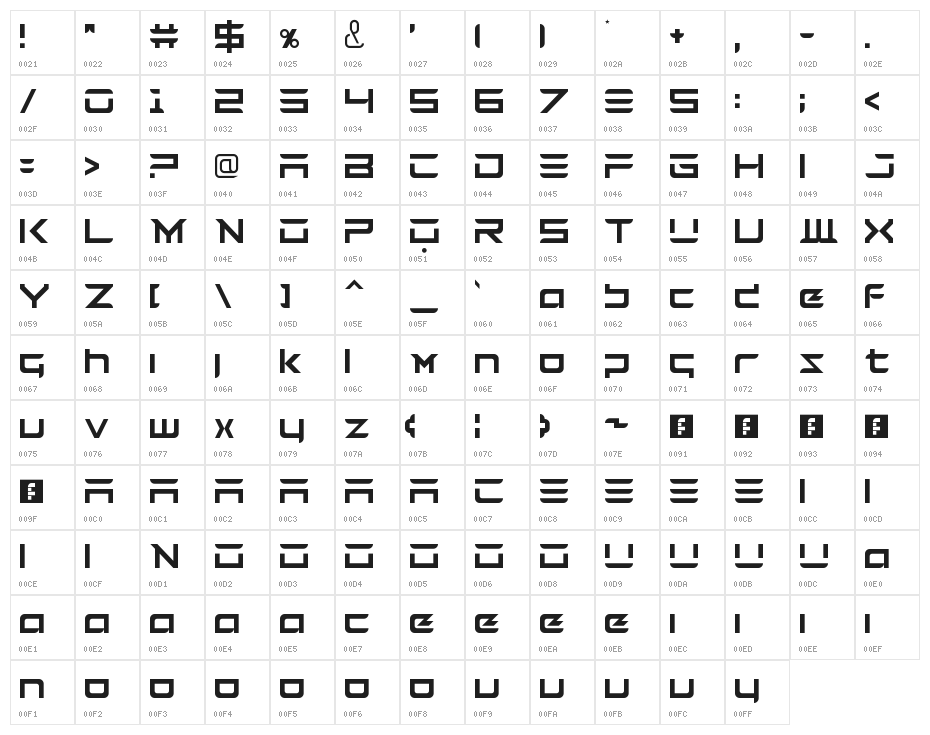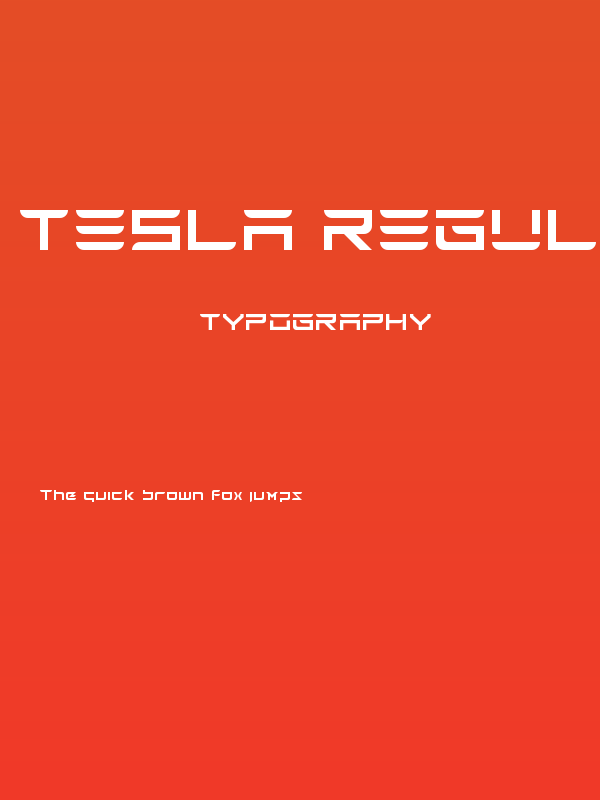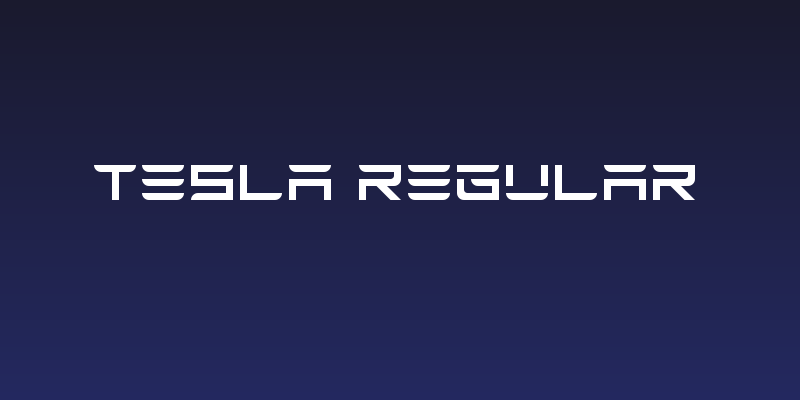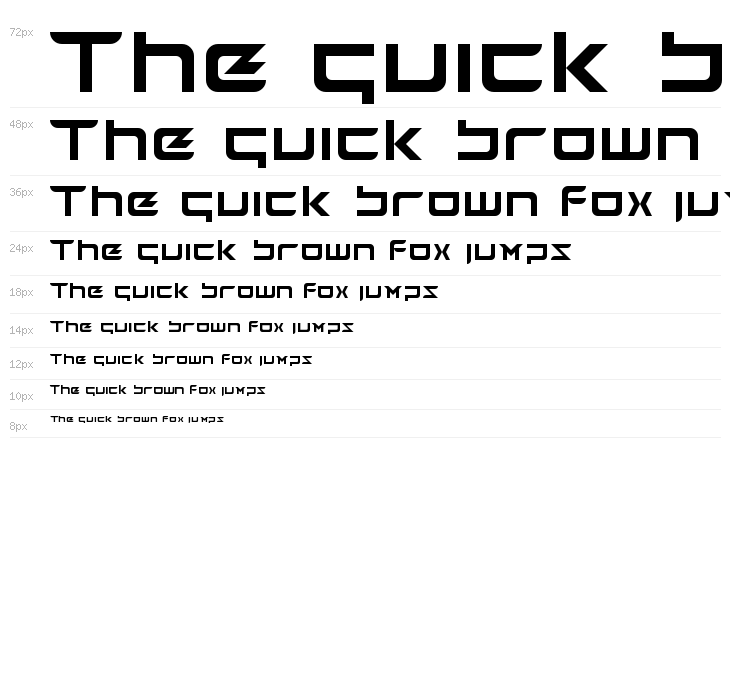
TESLA Regular Font
✎ Sci-fi
| Kategorien | Sci-fi |
| Anwendungsfall | Logos, Headlines, Branding |
| Vorgeschlagene Projekte | Ideal for technology branding, sci-fi themed designs, modern logos, and innovative product packaging. |